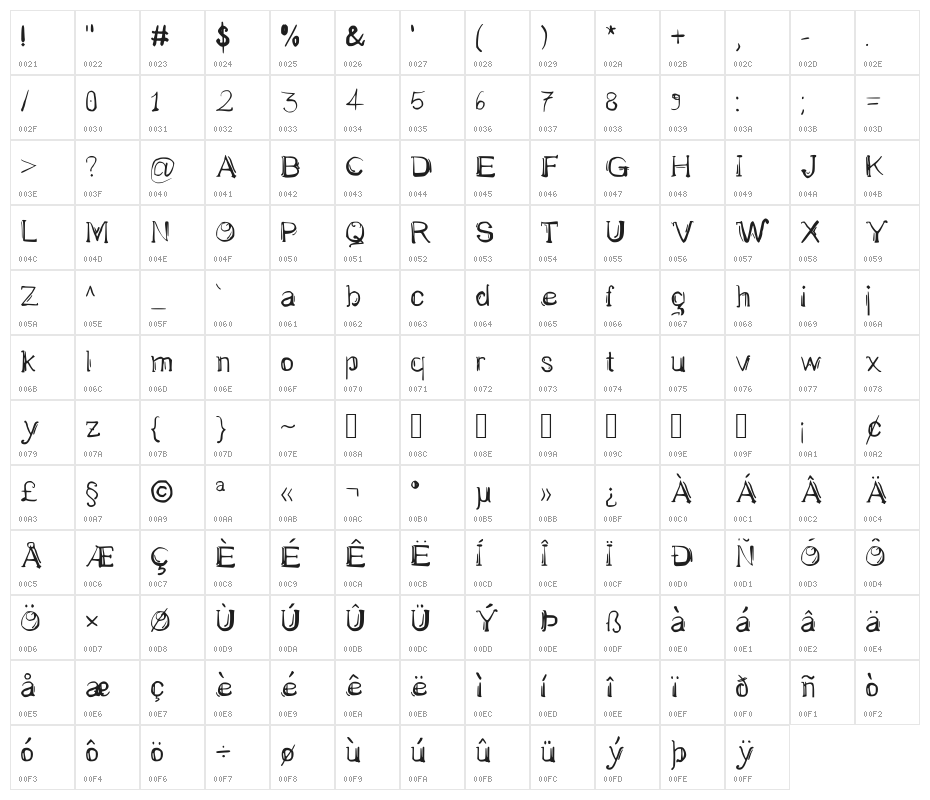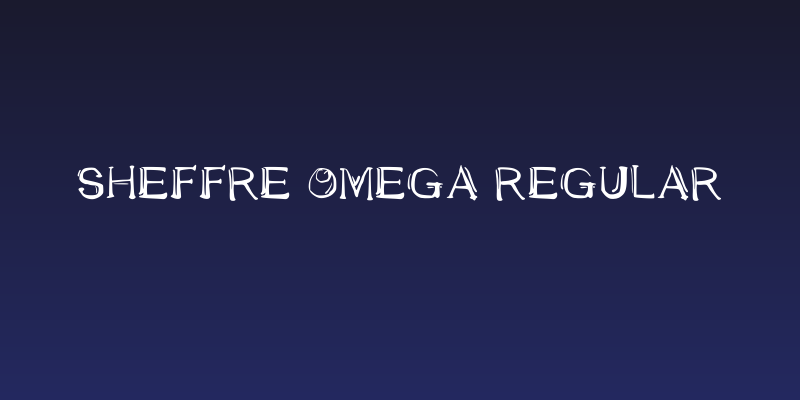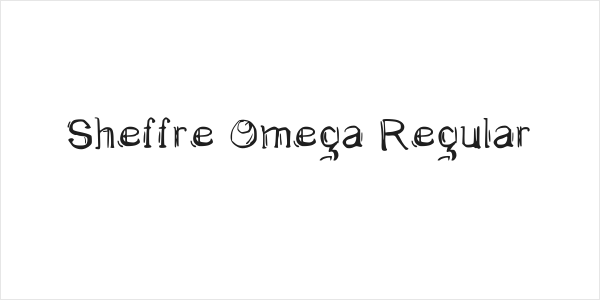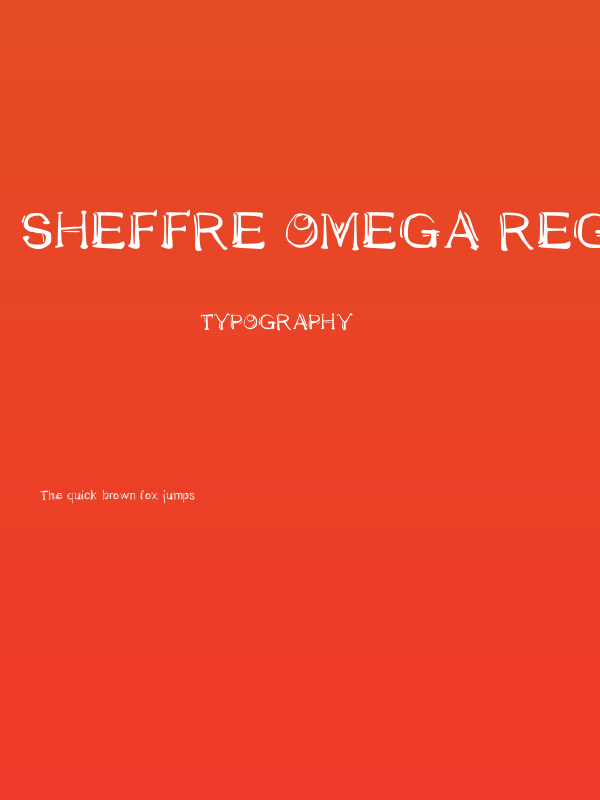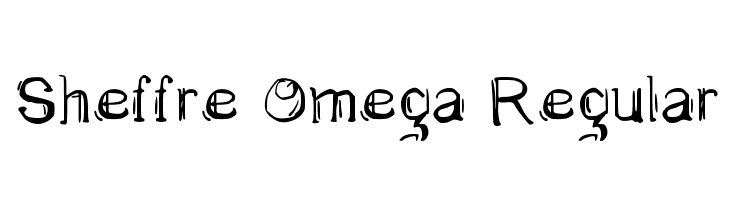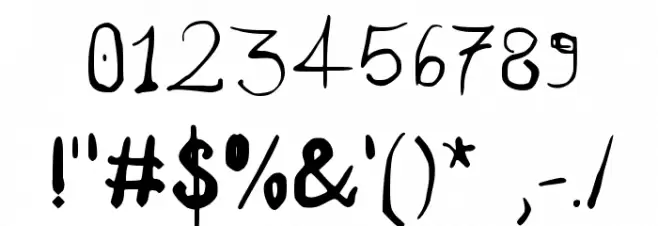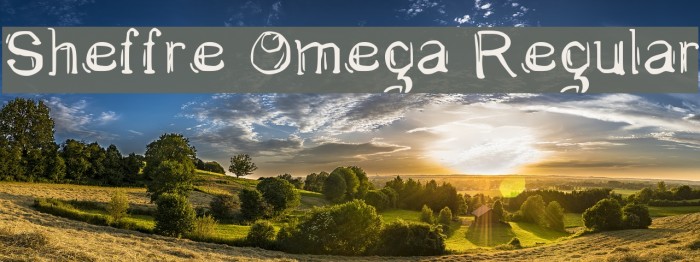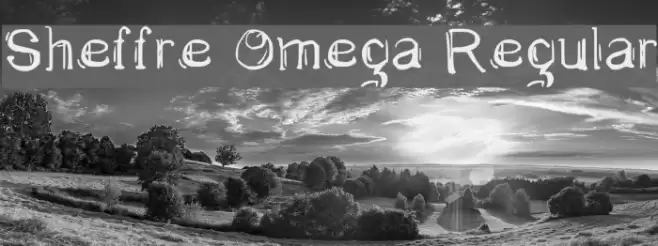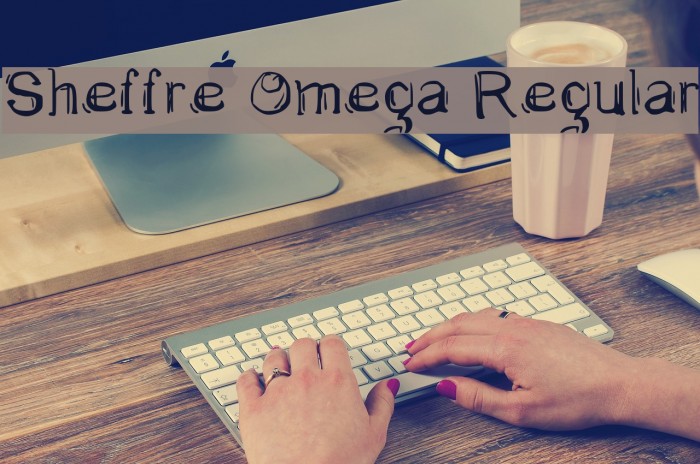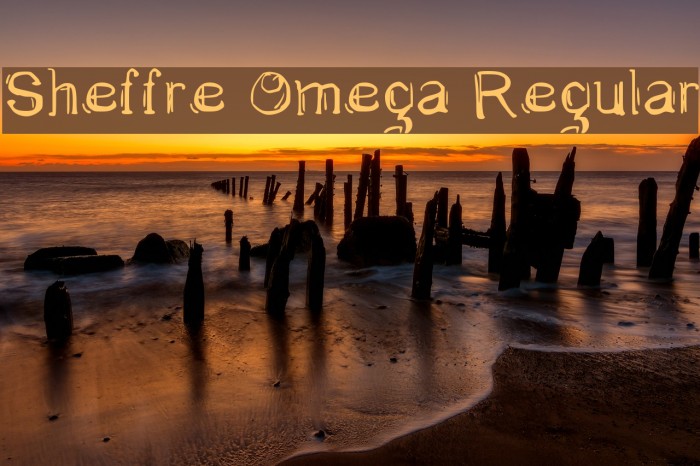
Sheffre Omega Regular Font
| Vorgeschlagene Projekte | Ideal for creative projects such as posters, album covers, branding for artistic ventures, or any design requiring a distinctive and eye-catching typeface. |